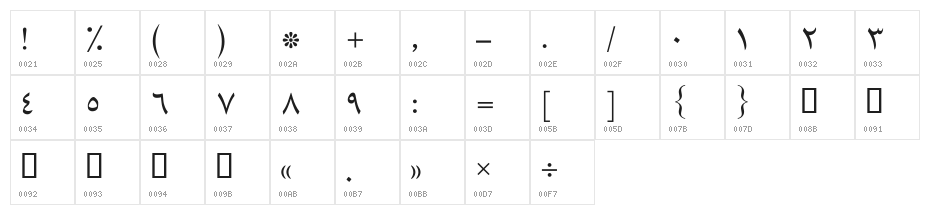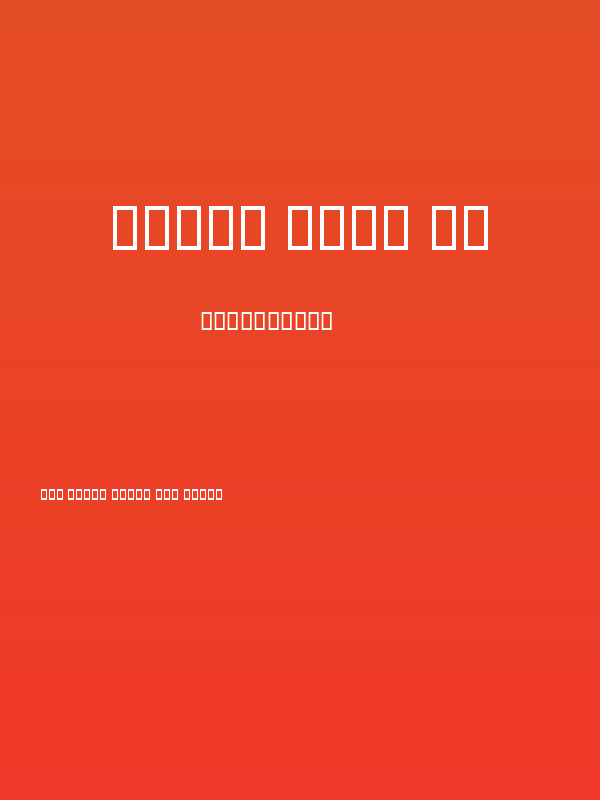
Naskh Type II Font
✎ Calligraphic
| Categorie | Calligraphic |
| Caso d'uso | Logos, Invitations, Artistic projects |
| Progetti proposti | Ideal for cultural publications, formal invitations, and artistic projects that require a sophisticated touch. |